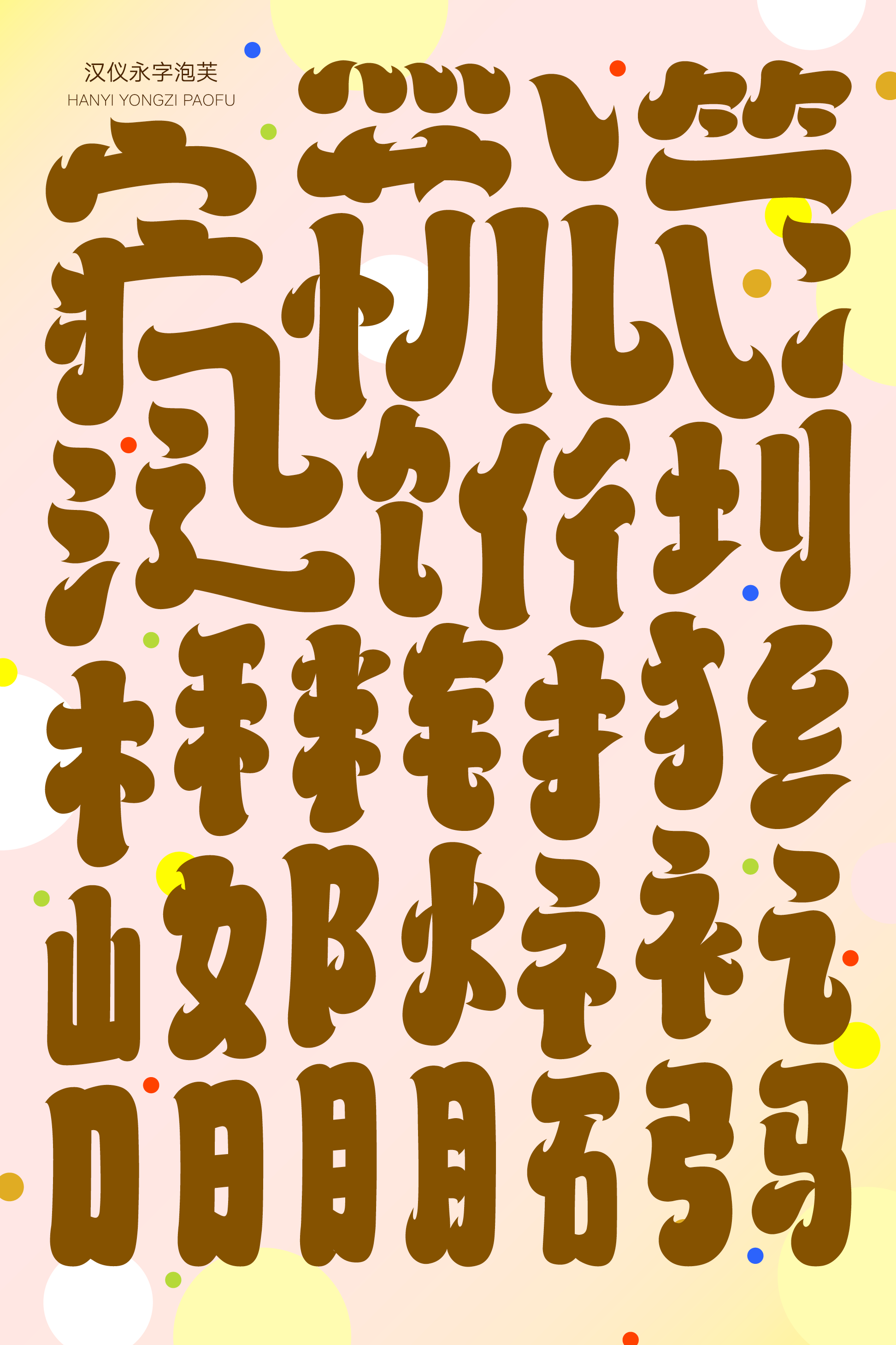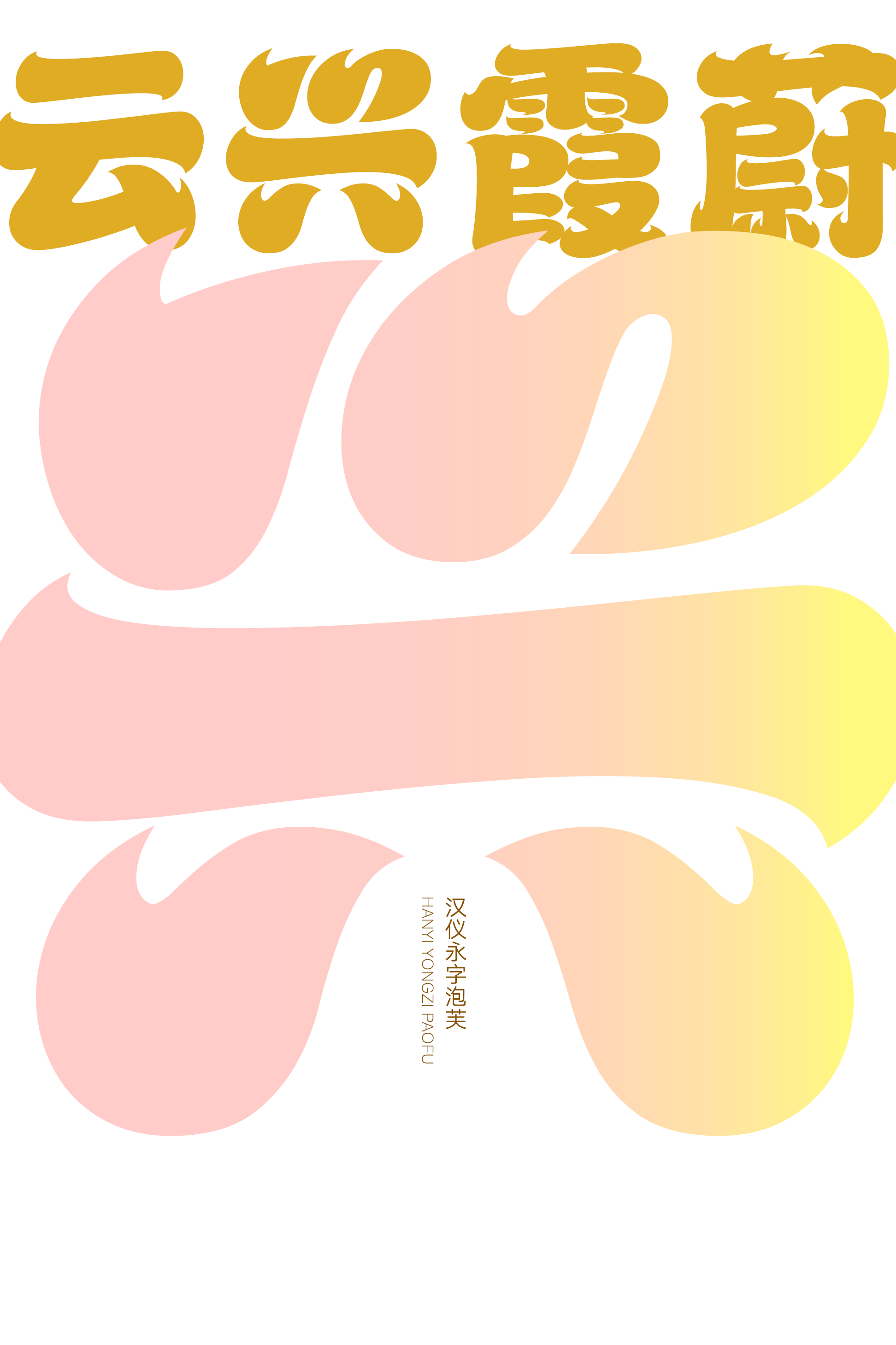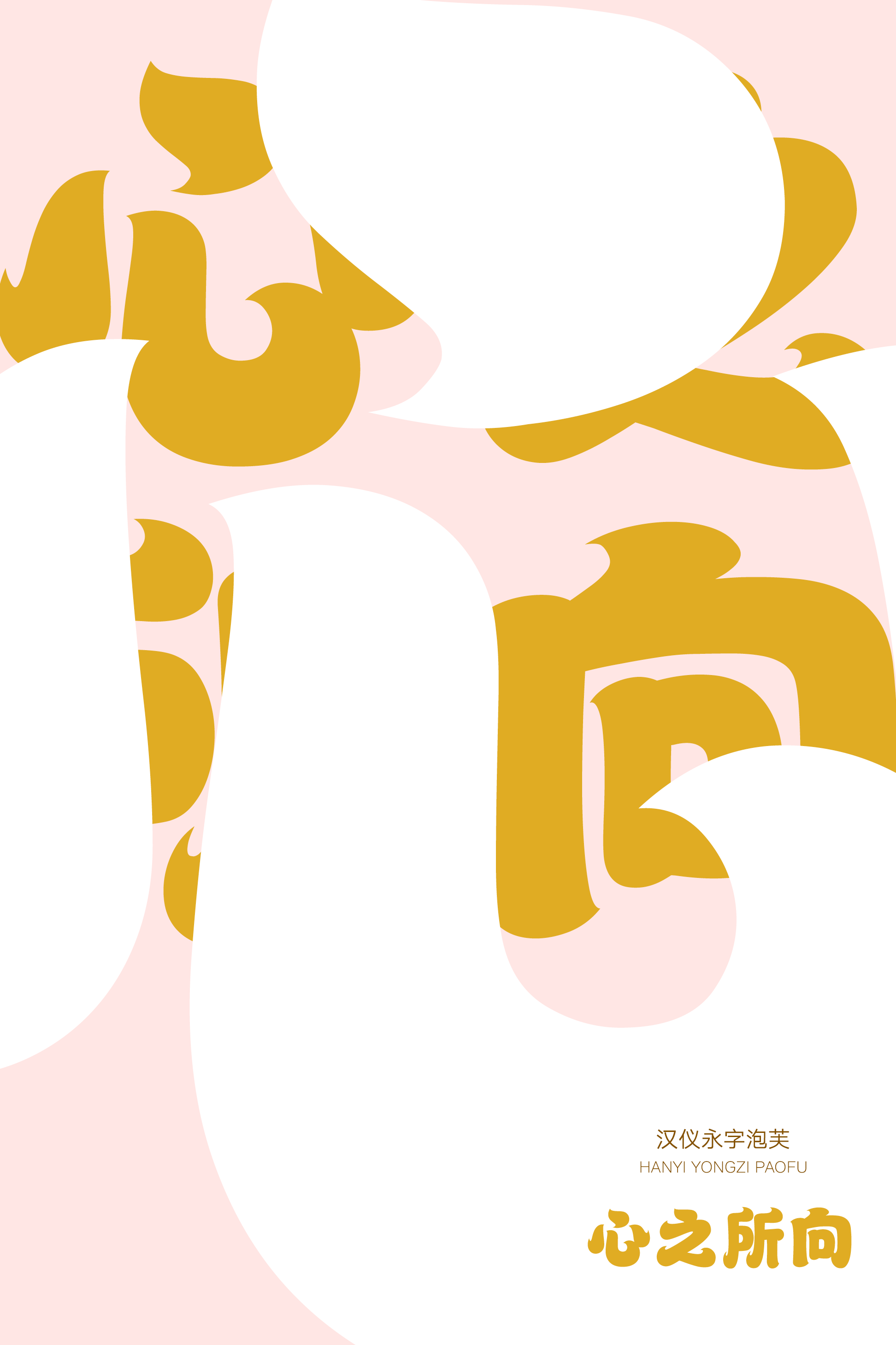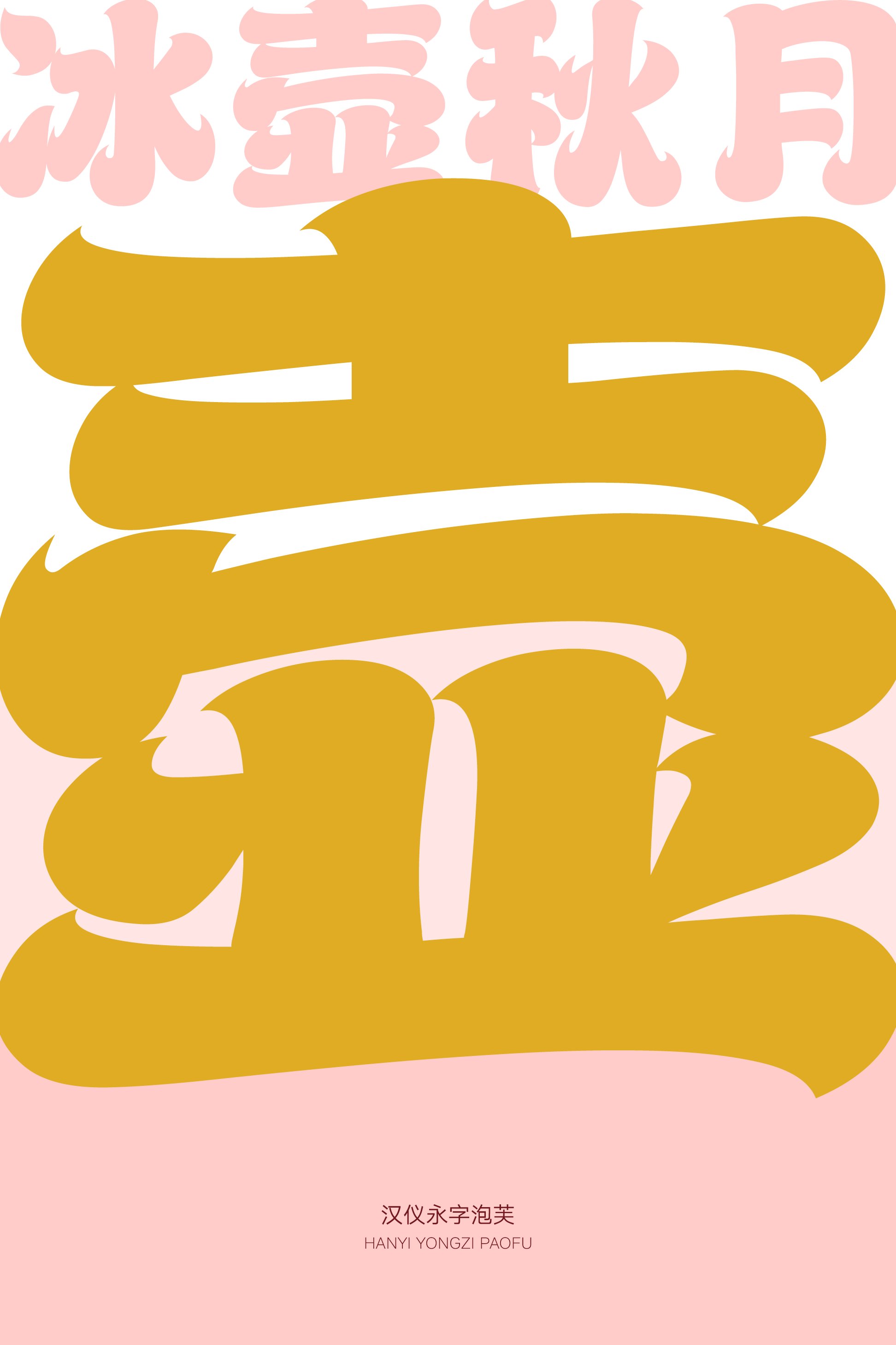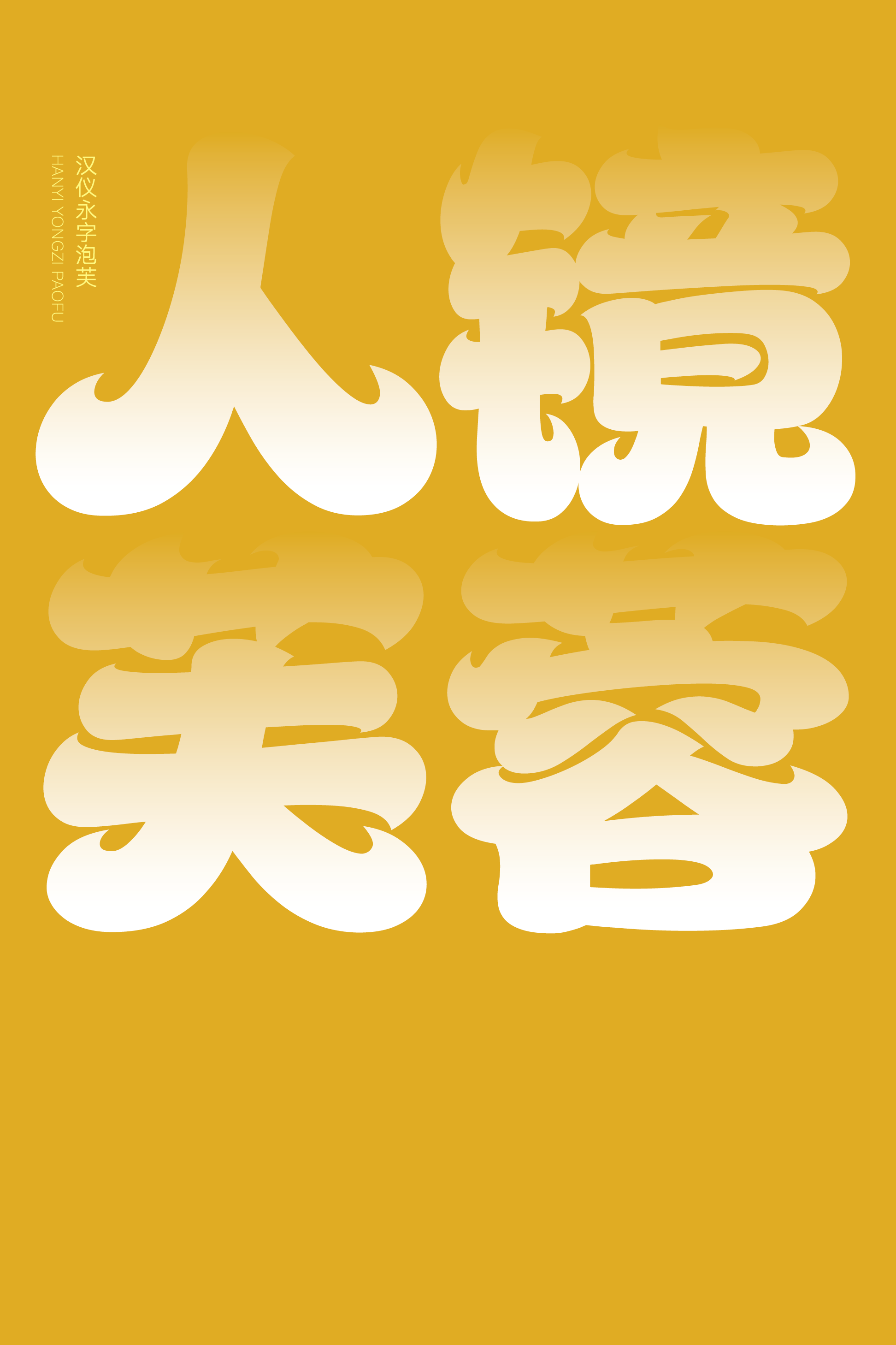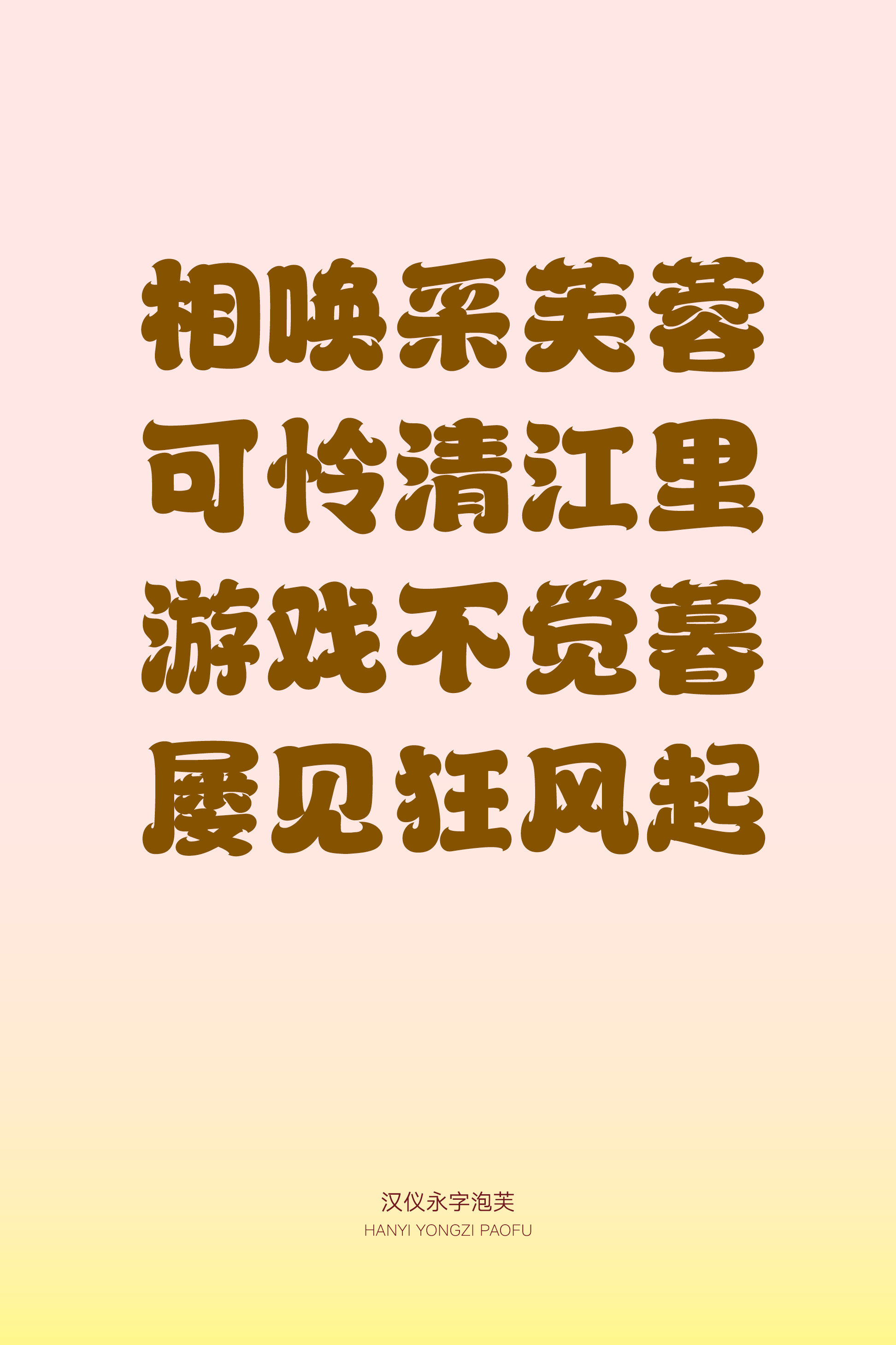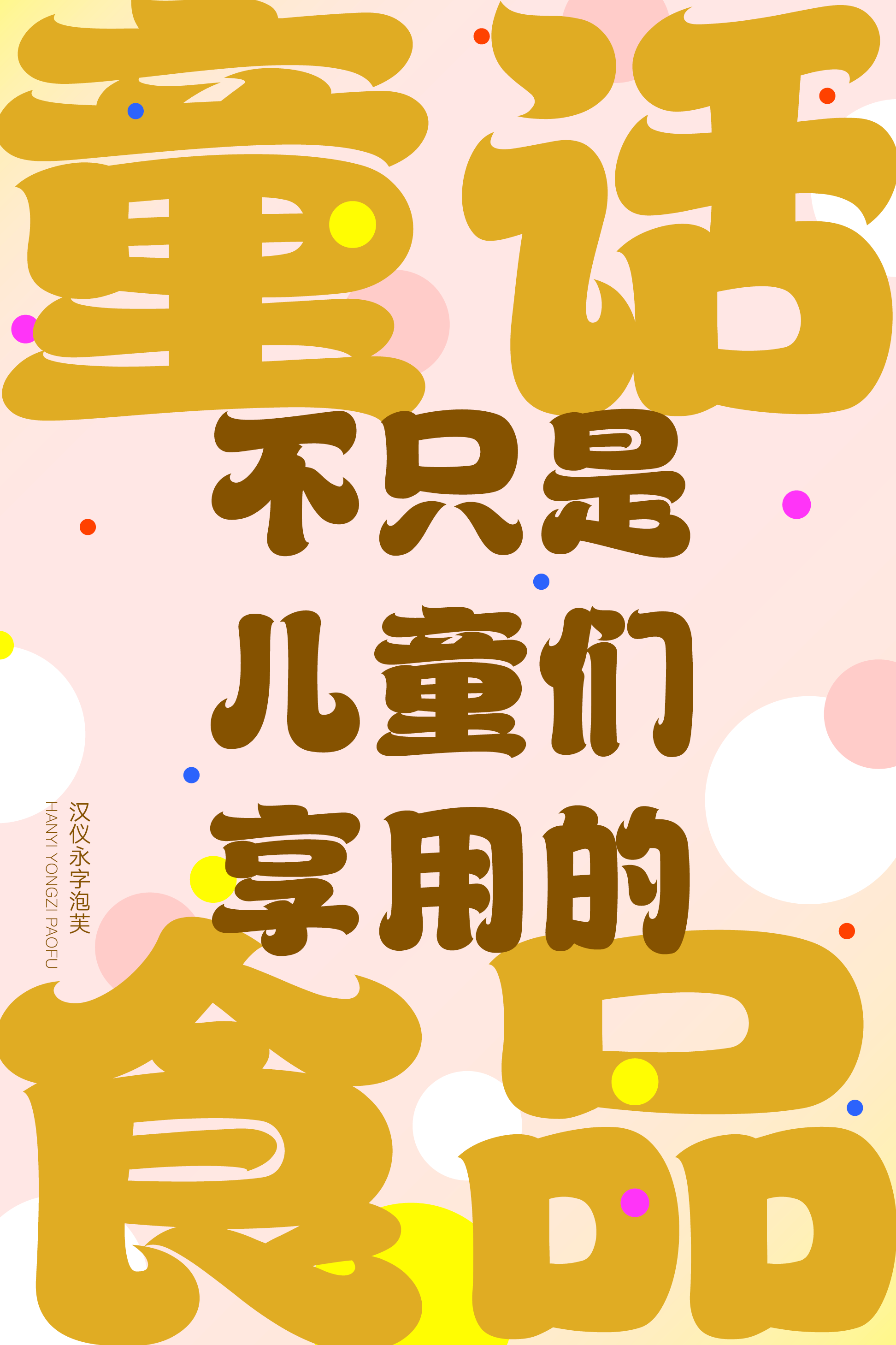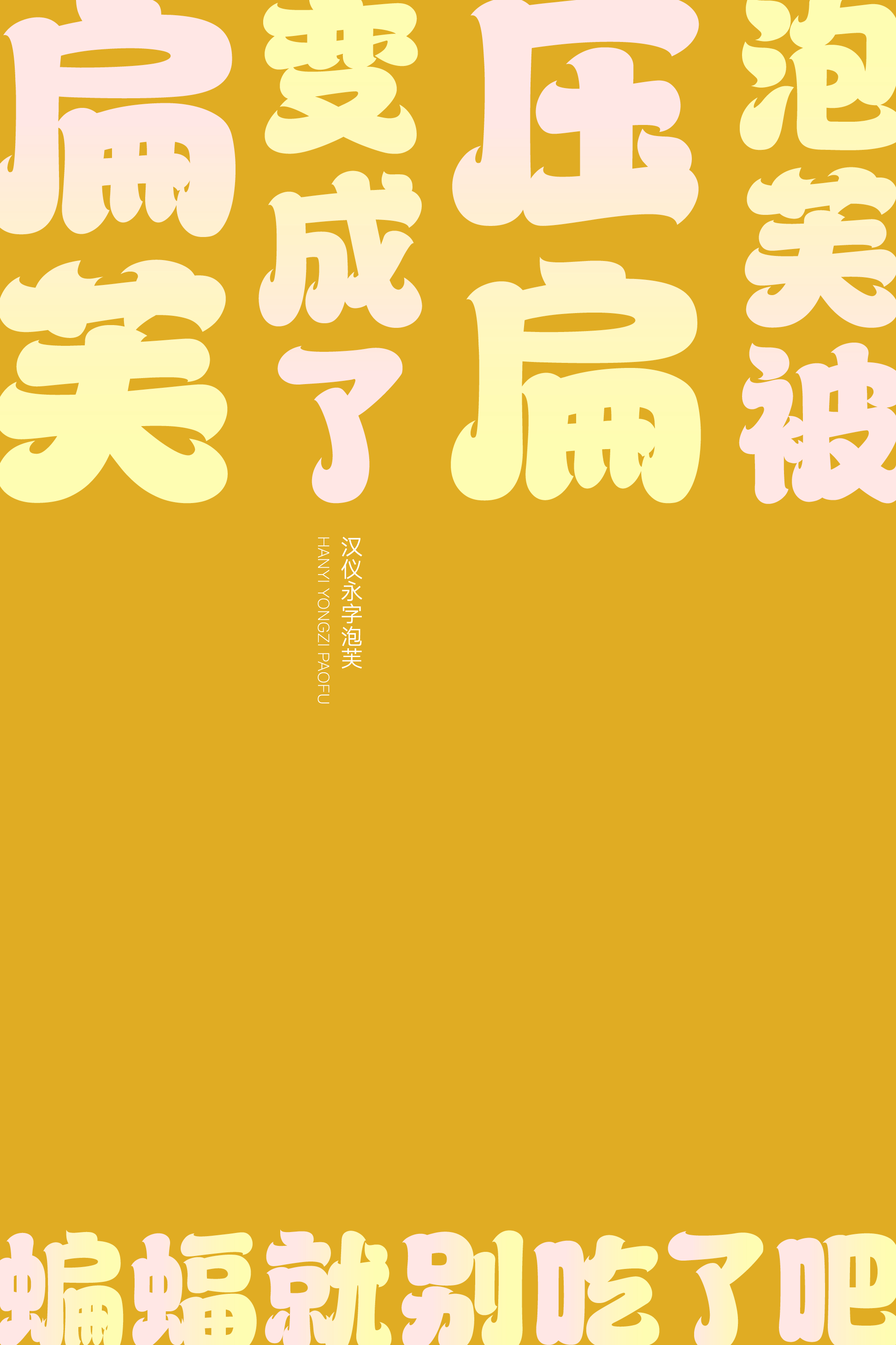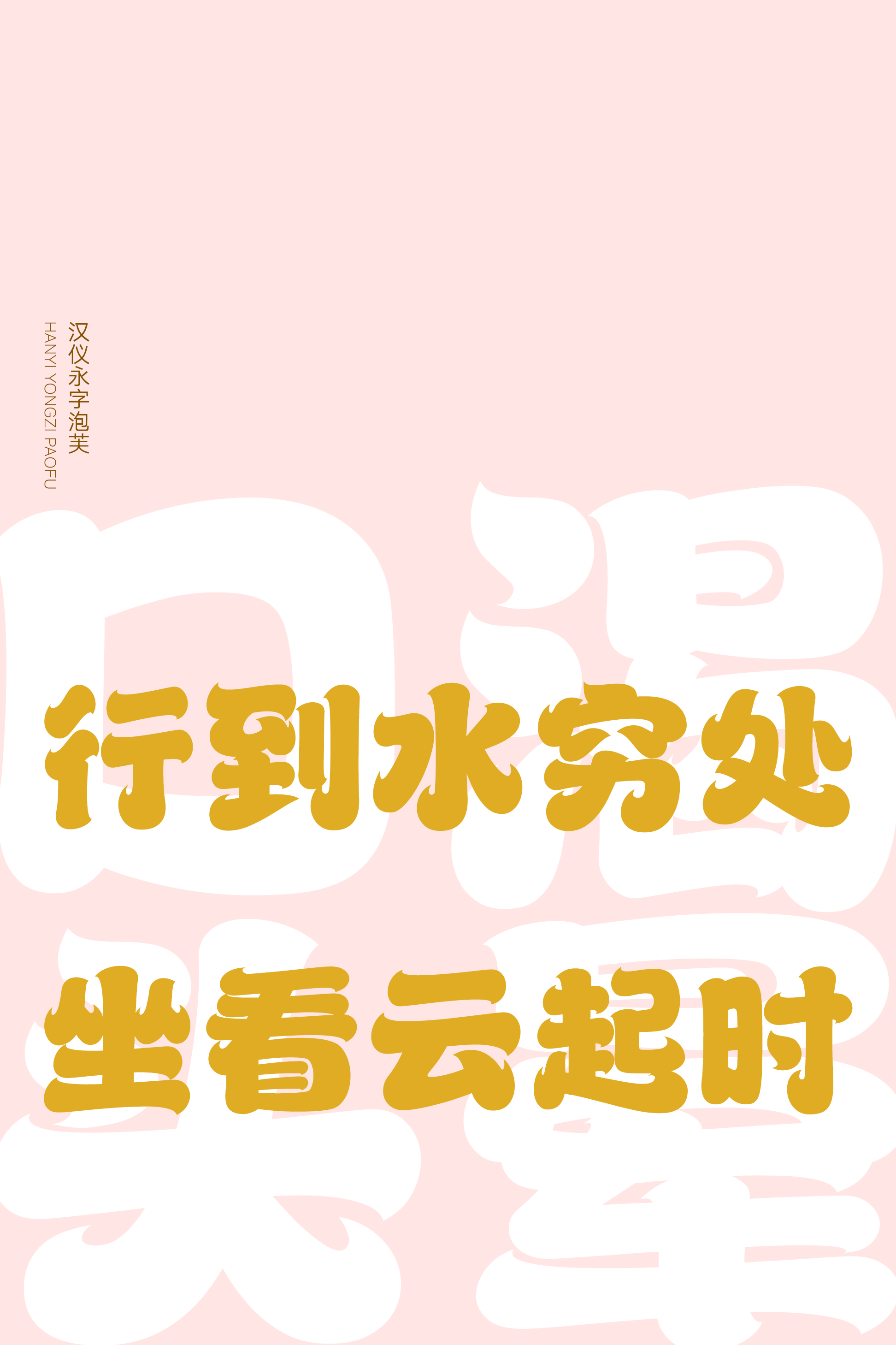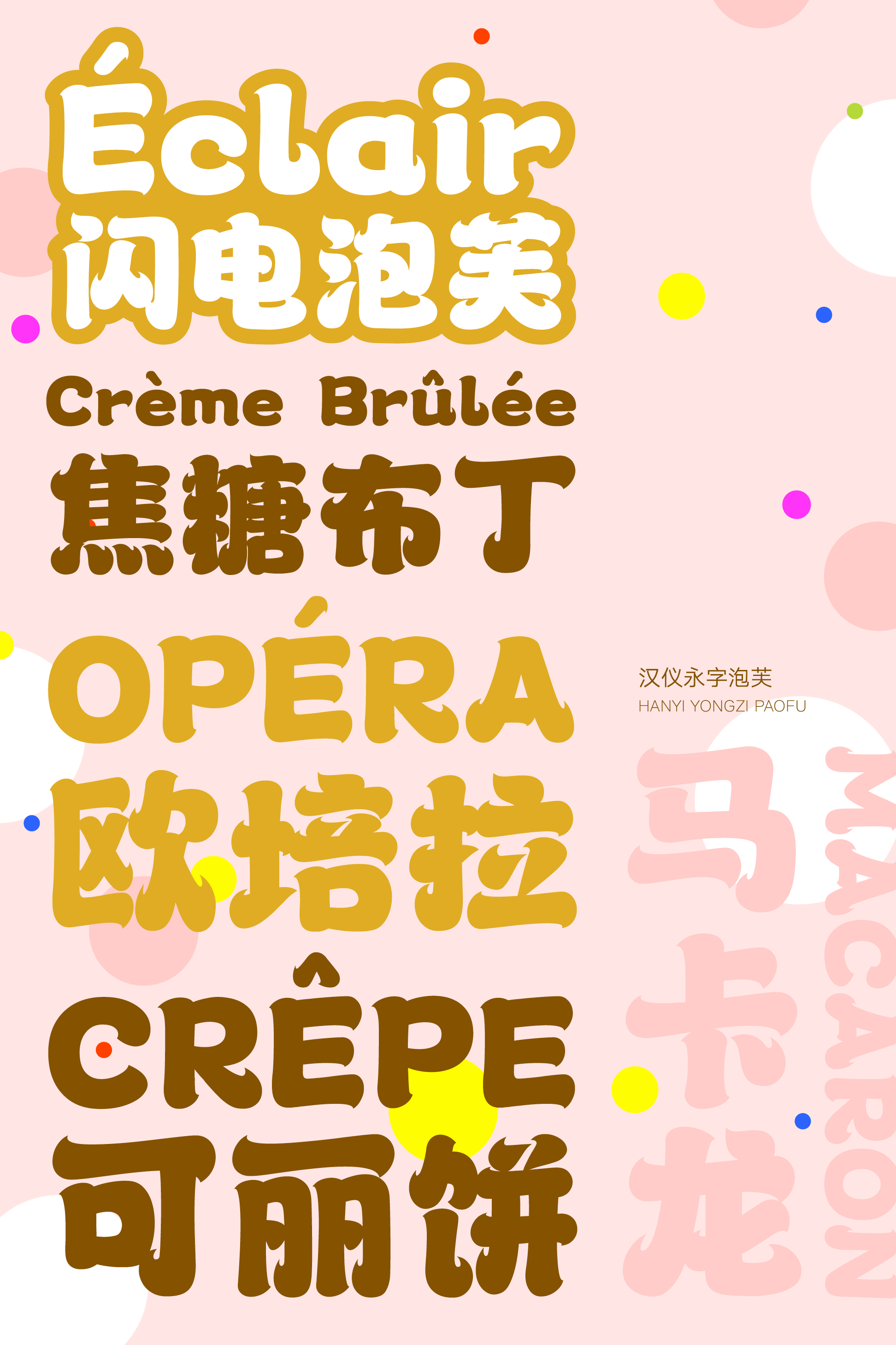
汉仪永字泡芙
软乎乎的汉仪永字泡芙,造型饱满、曲线柔软,由奶油般的笔画构成,起收笔的出锋颇具手写感,好像诱人的奶油尖尖,让人想要一口一个字,大饱眼福。这款字体适合作为标题字体应用于食品包装、餐饮广告等使用场景,谁看了这么蓬松柔软的泡芙能不嘴馋呢?
字形和泡芙一样圆而蓬松,一口泡芙一个字。
笔画饱满、柔软、轻盈,如同泡芙的奶油内馅。
起笔的小钩和收笔的回锋颇具手写感,像是诱人的奶油尖尖。
西文部分也是由泡芙般圆滚滚的造型、奶油般软乎乎的笔画构成,看起来就很好“吃”。